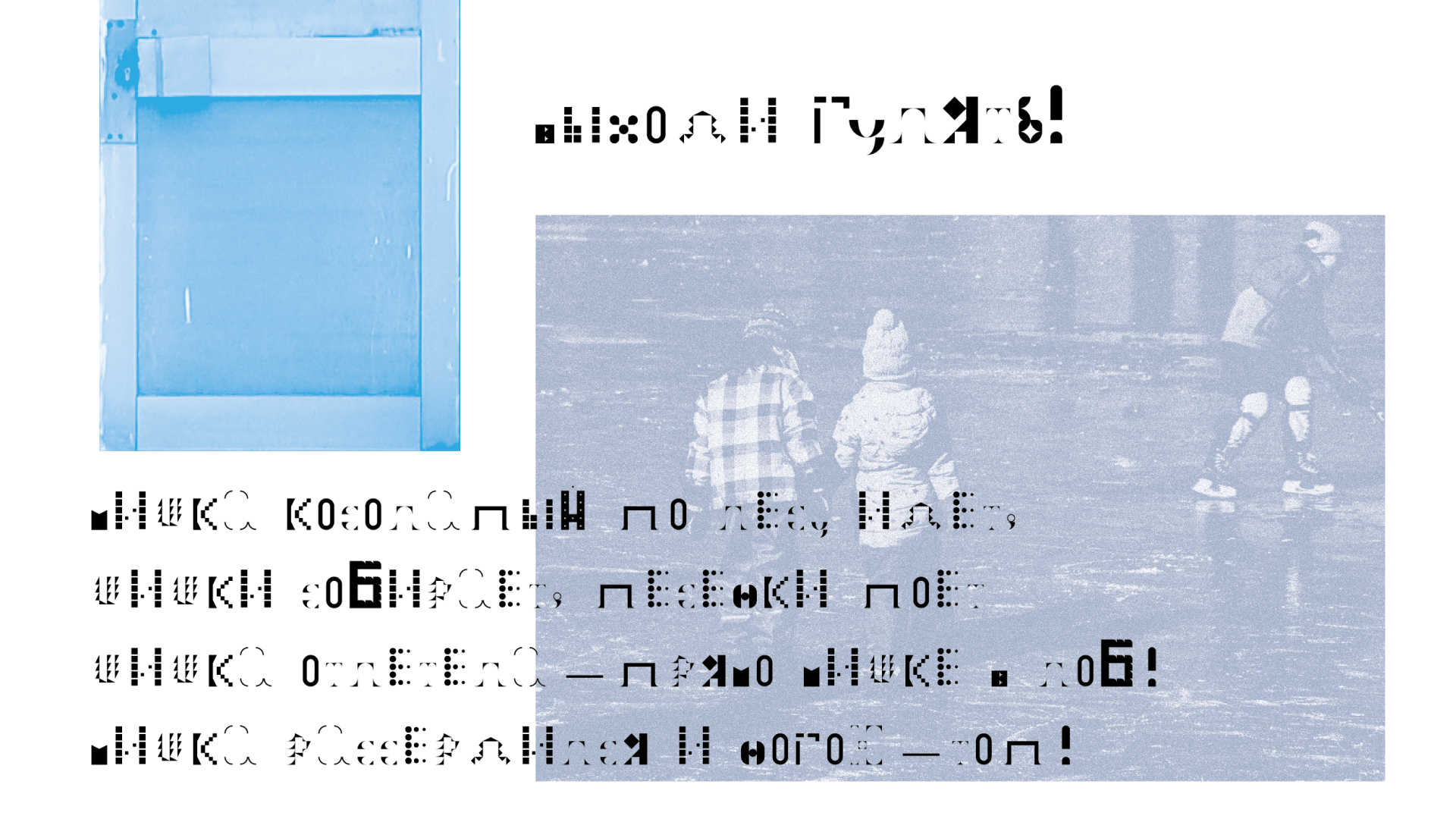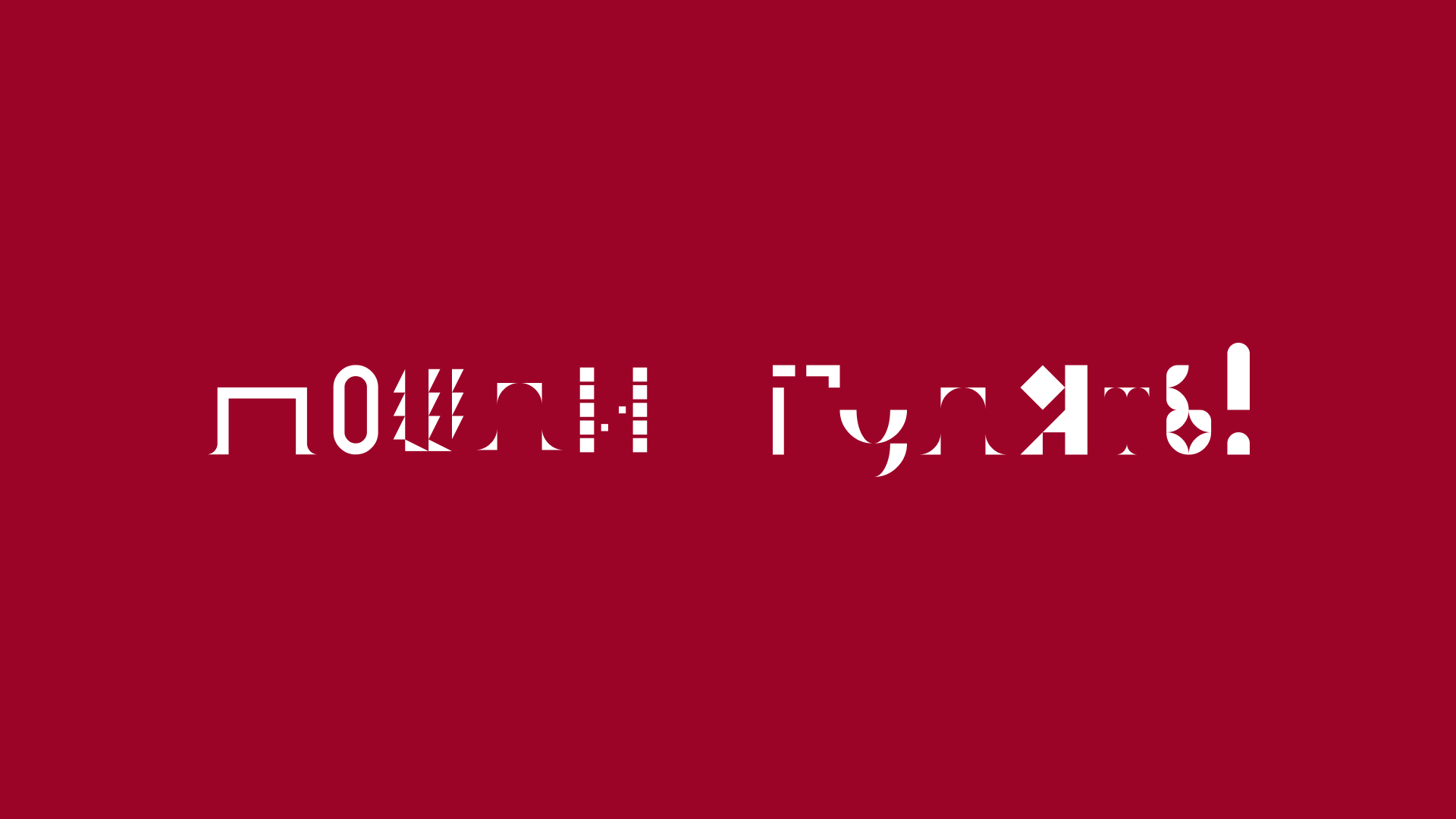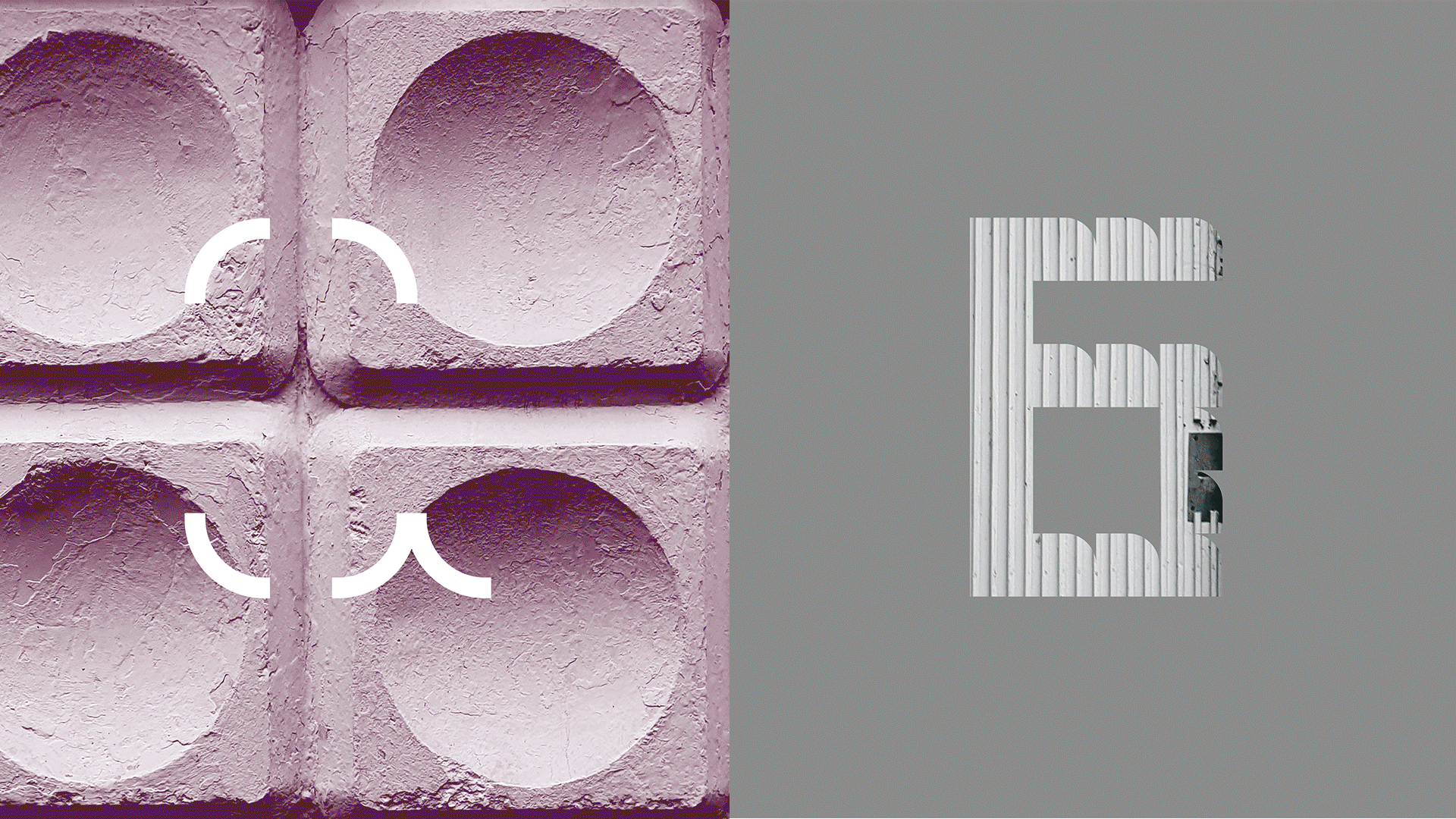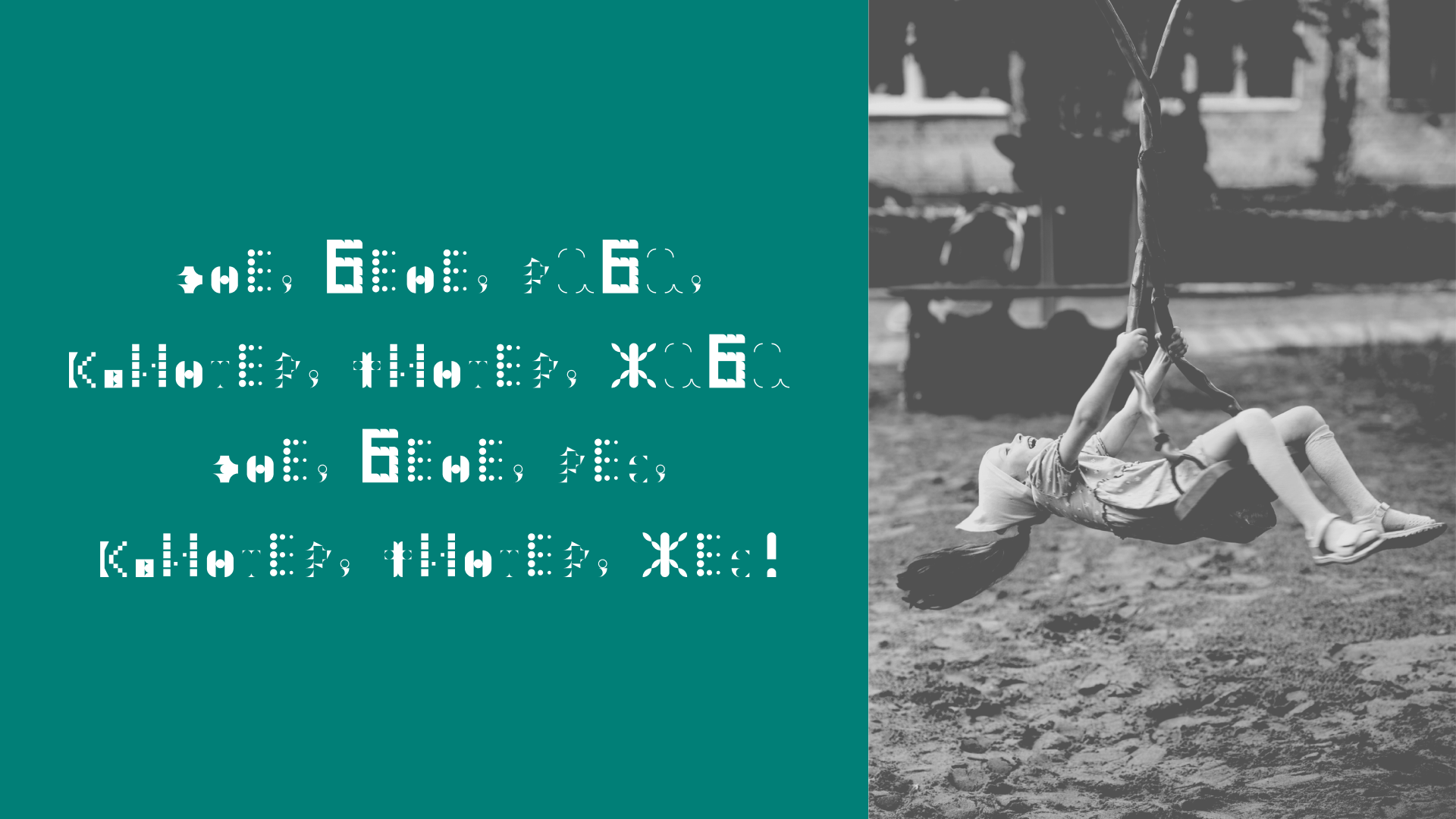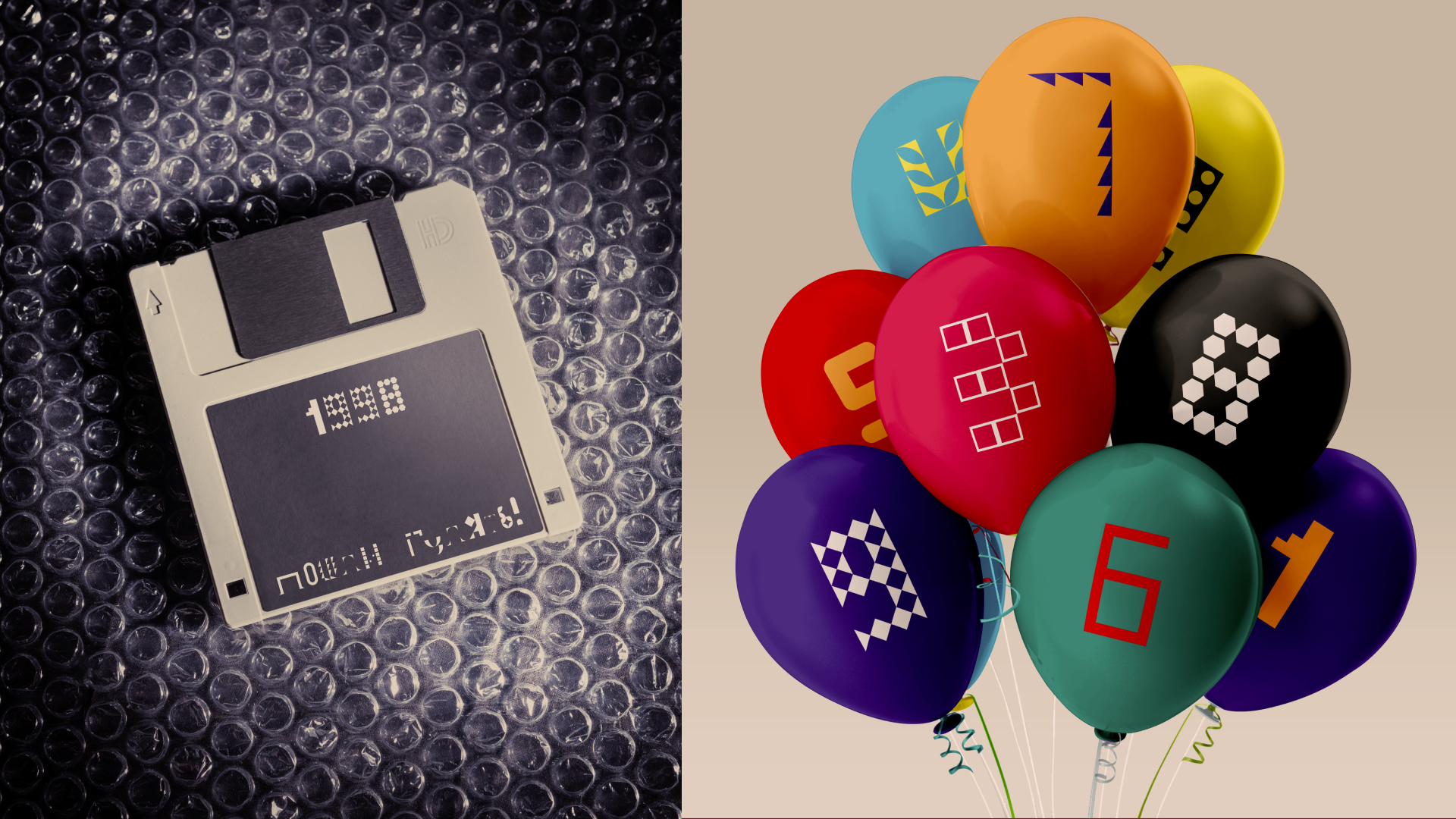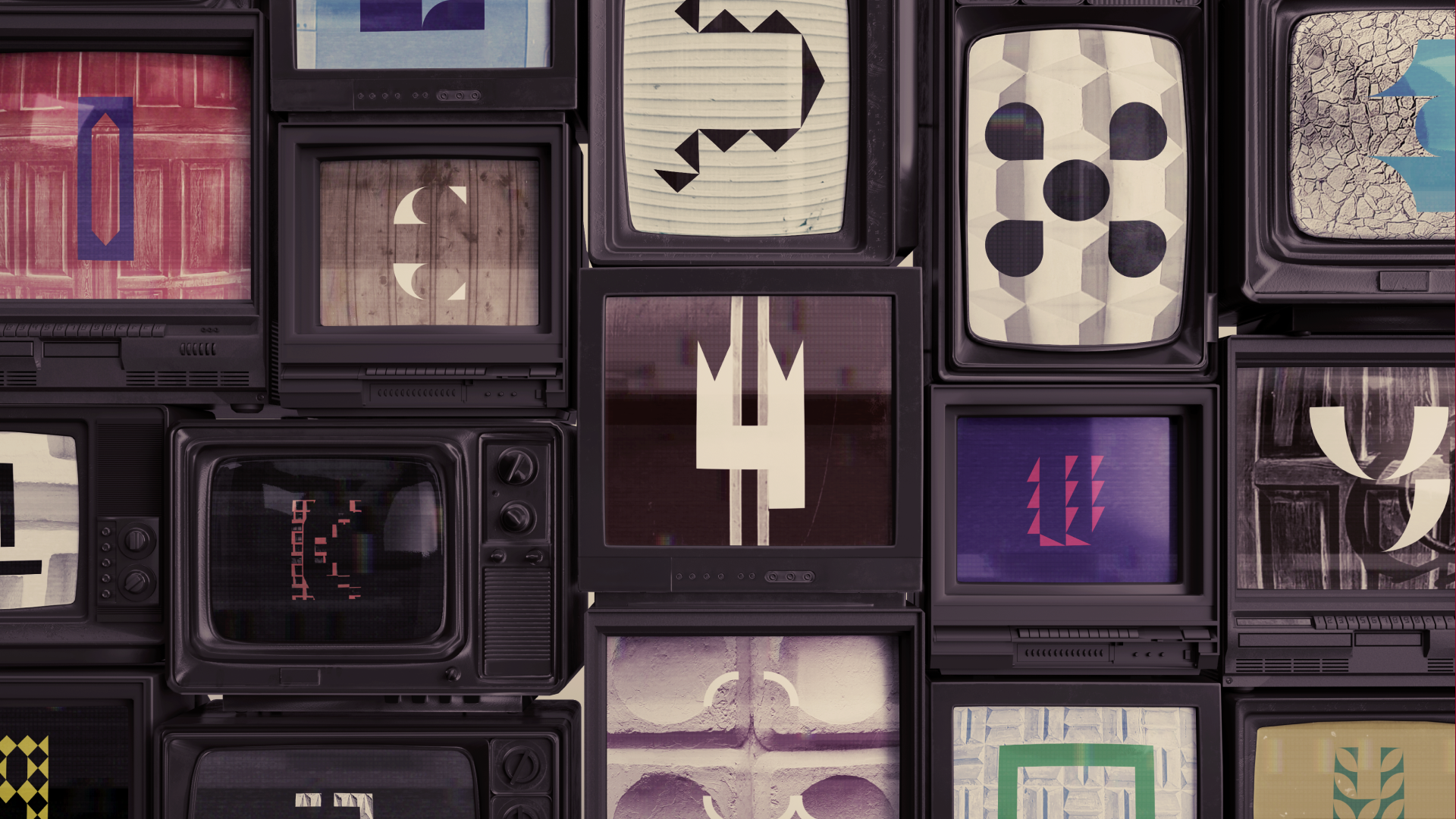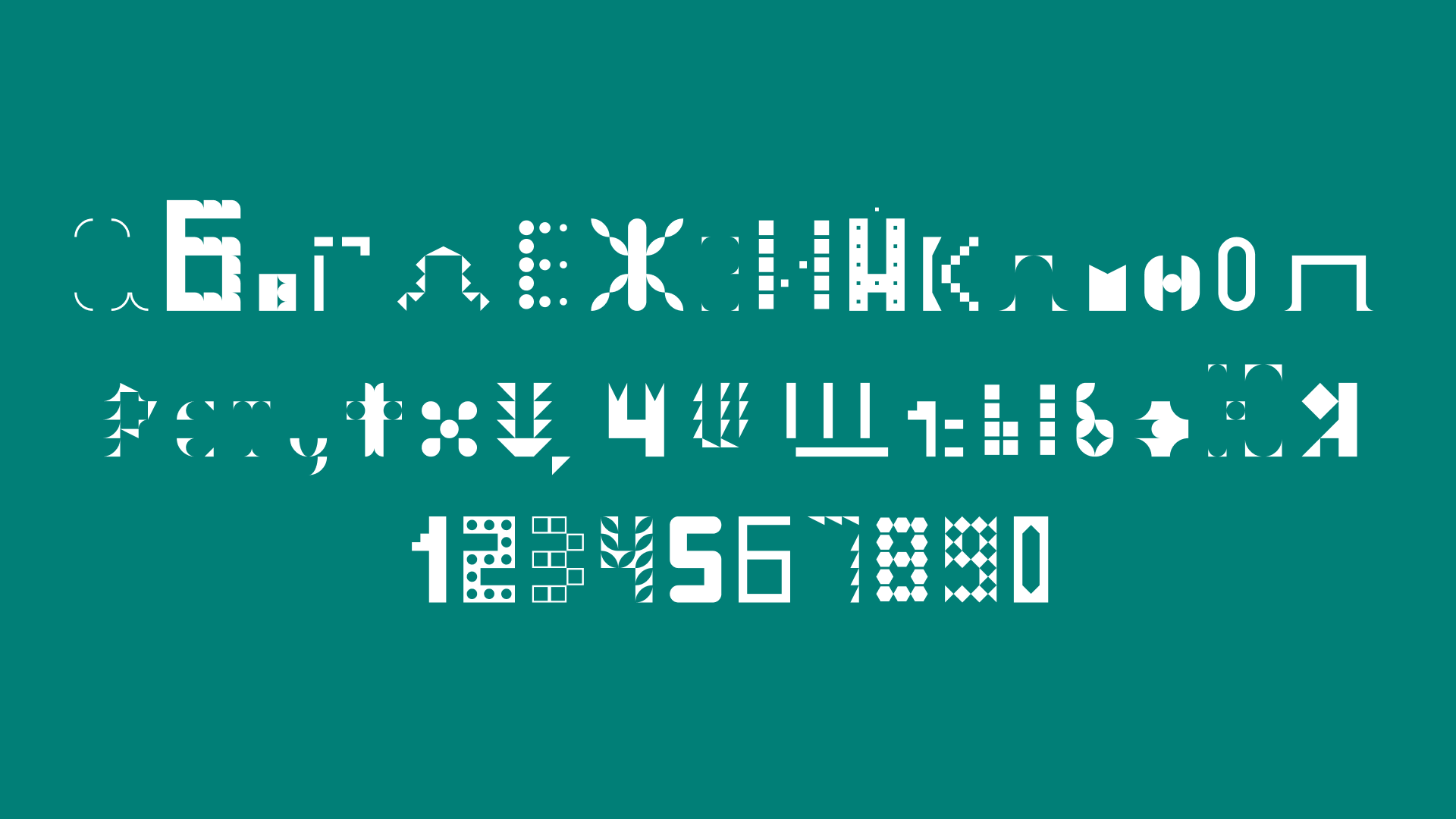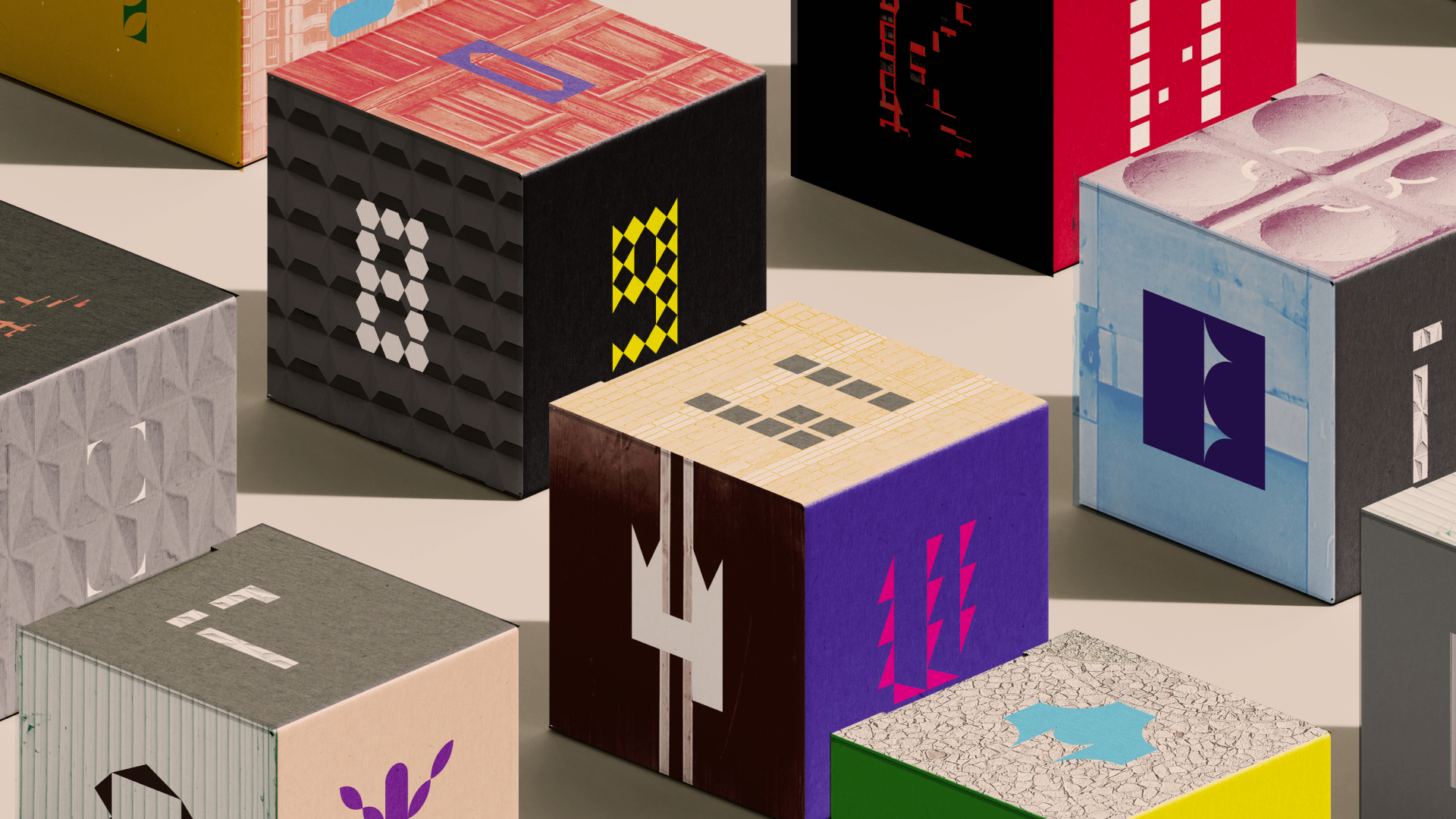
Экспериментальный шрифт
Пошли гулять: ностальгический шрифт
Пошли гулять — экспериментальный шрифт, основанный на чувстве ностальгии по детству.
Изначально идея пришла в процессе экспериментов с модульными шрифтами. Он напомнил о шифрах и записках, которые мы писали в детстве.
В шрифте нет одинаковых знаков — каждый из них имеет свой характер, ассоциации и момент. Нарочито неровный, он заводной и местами наивный.